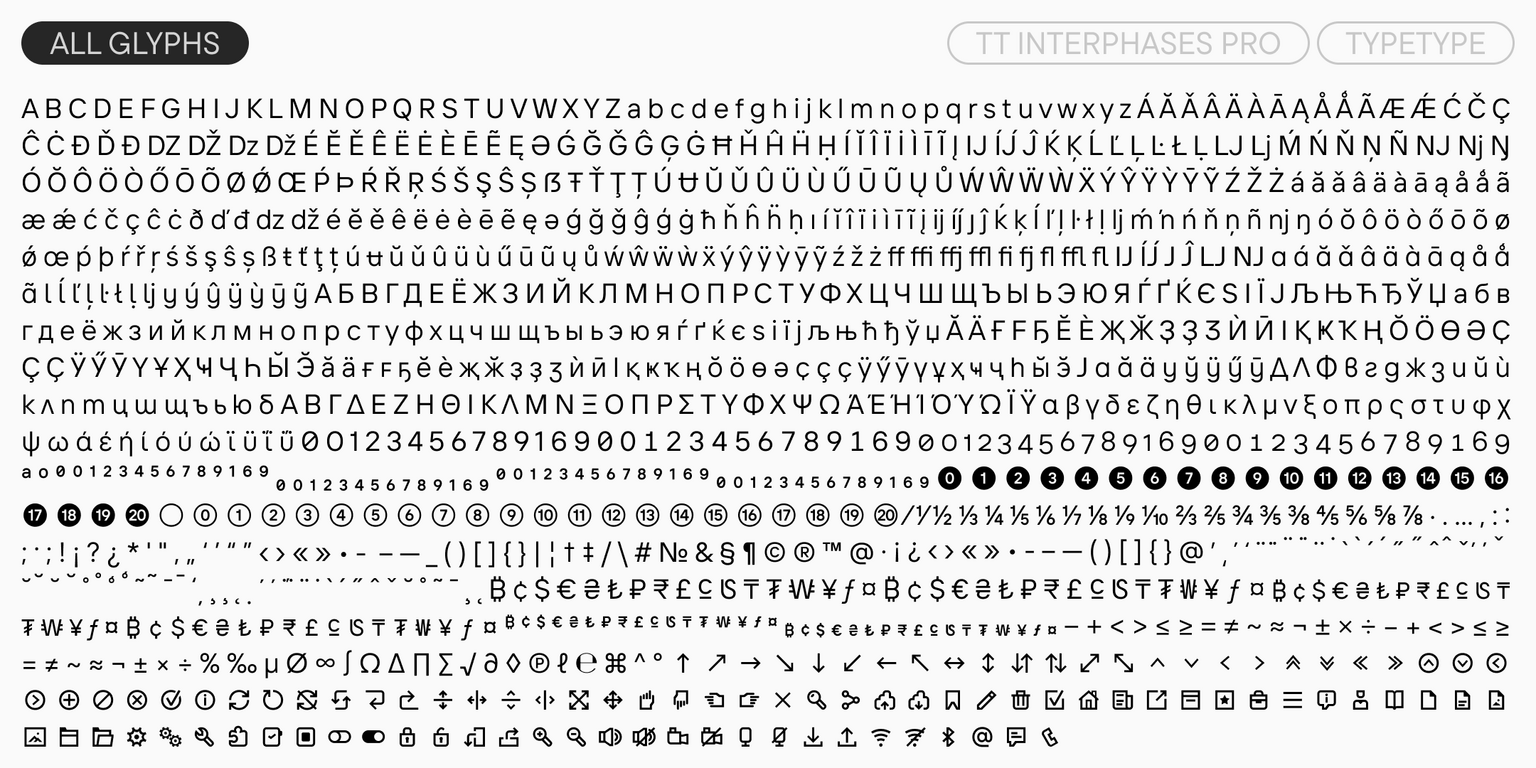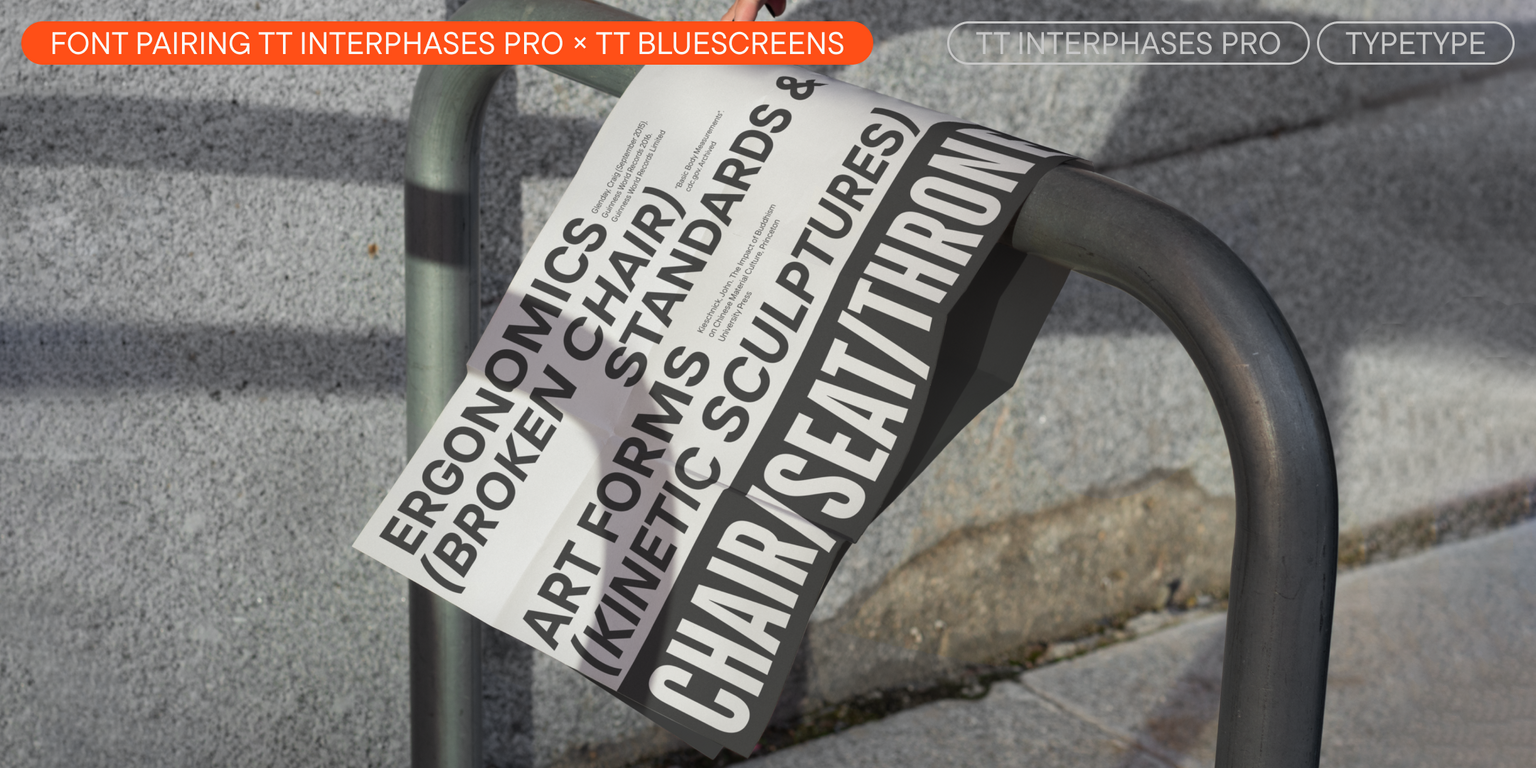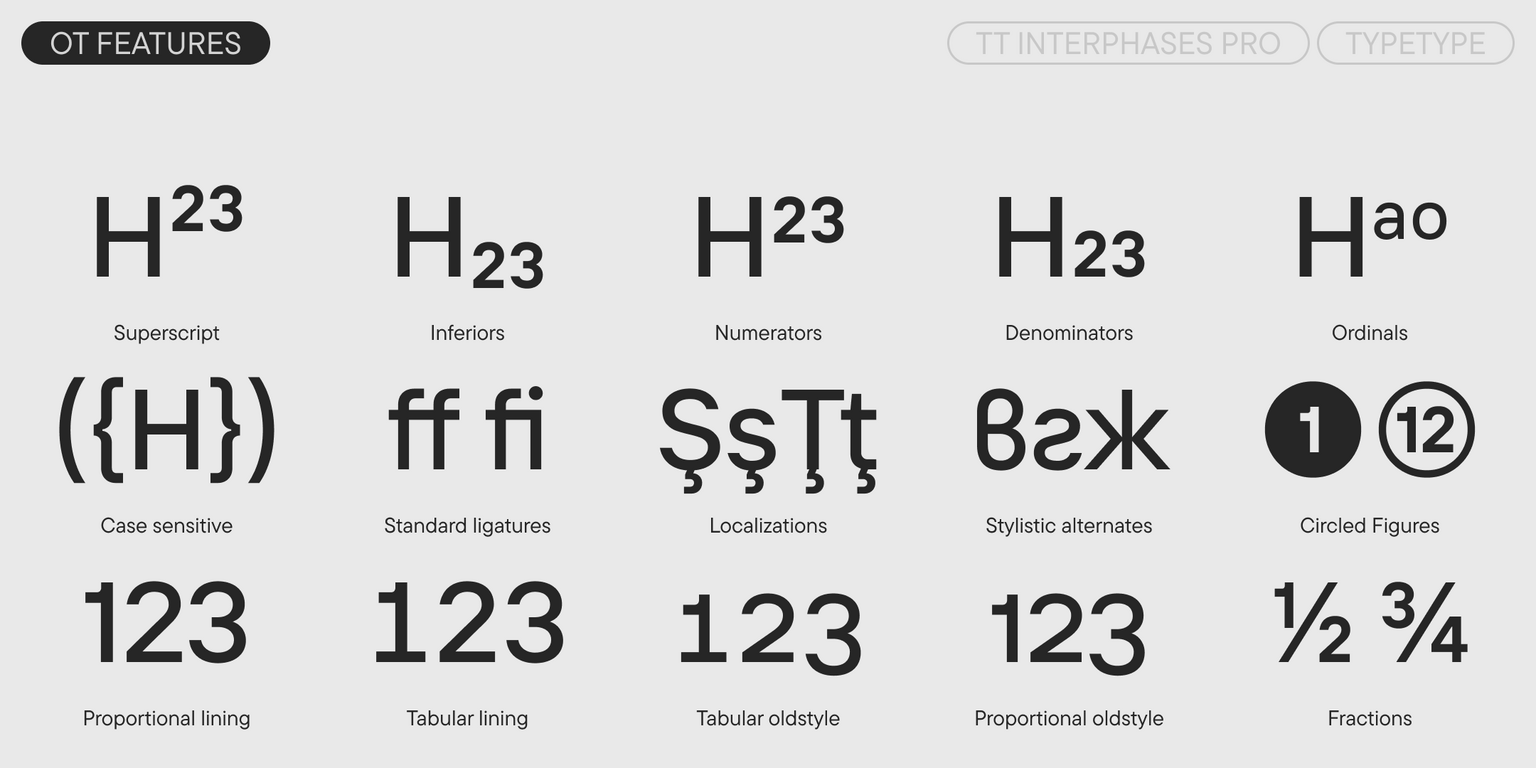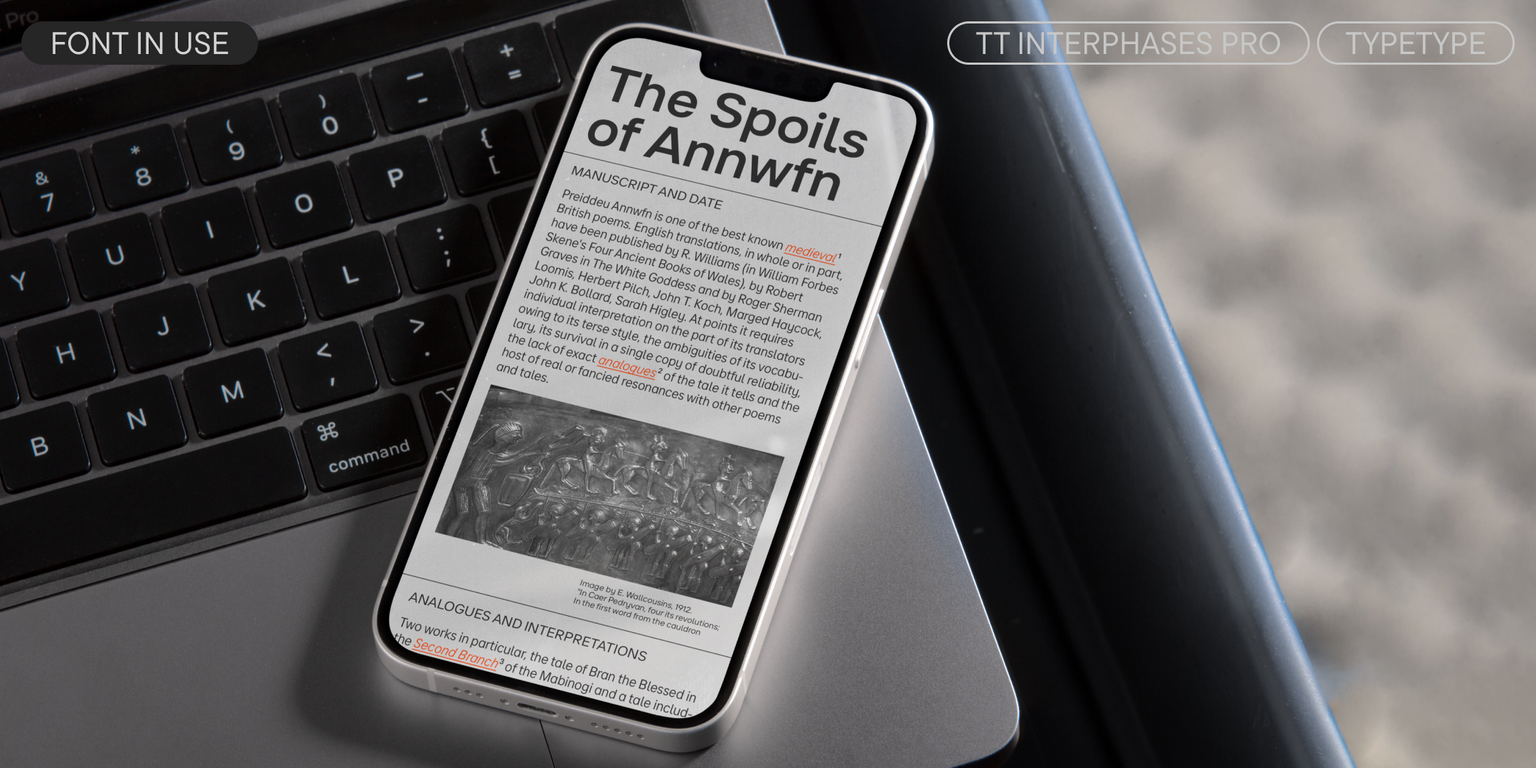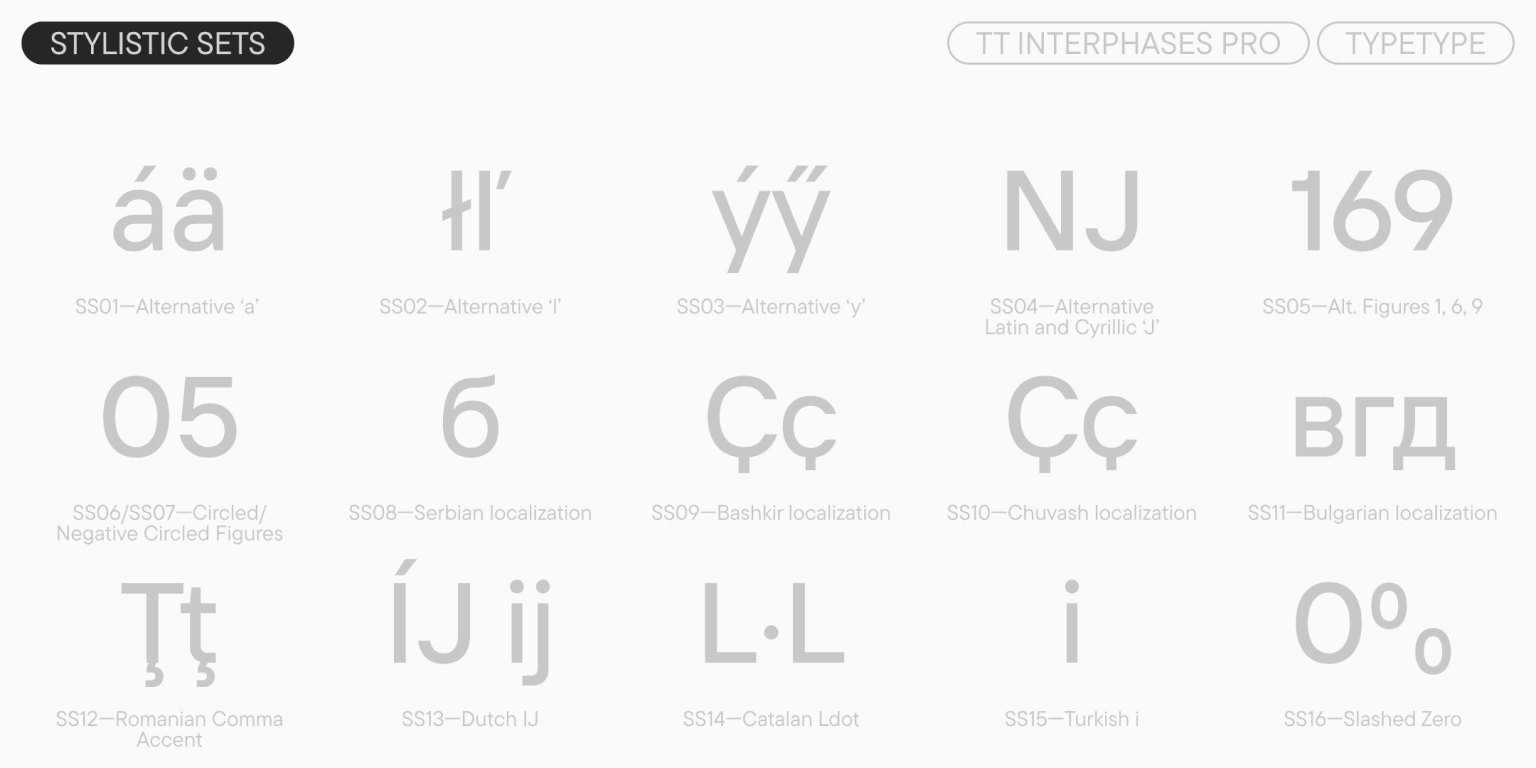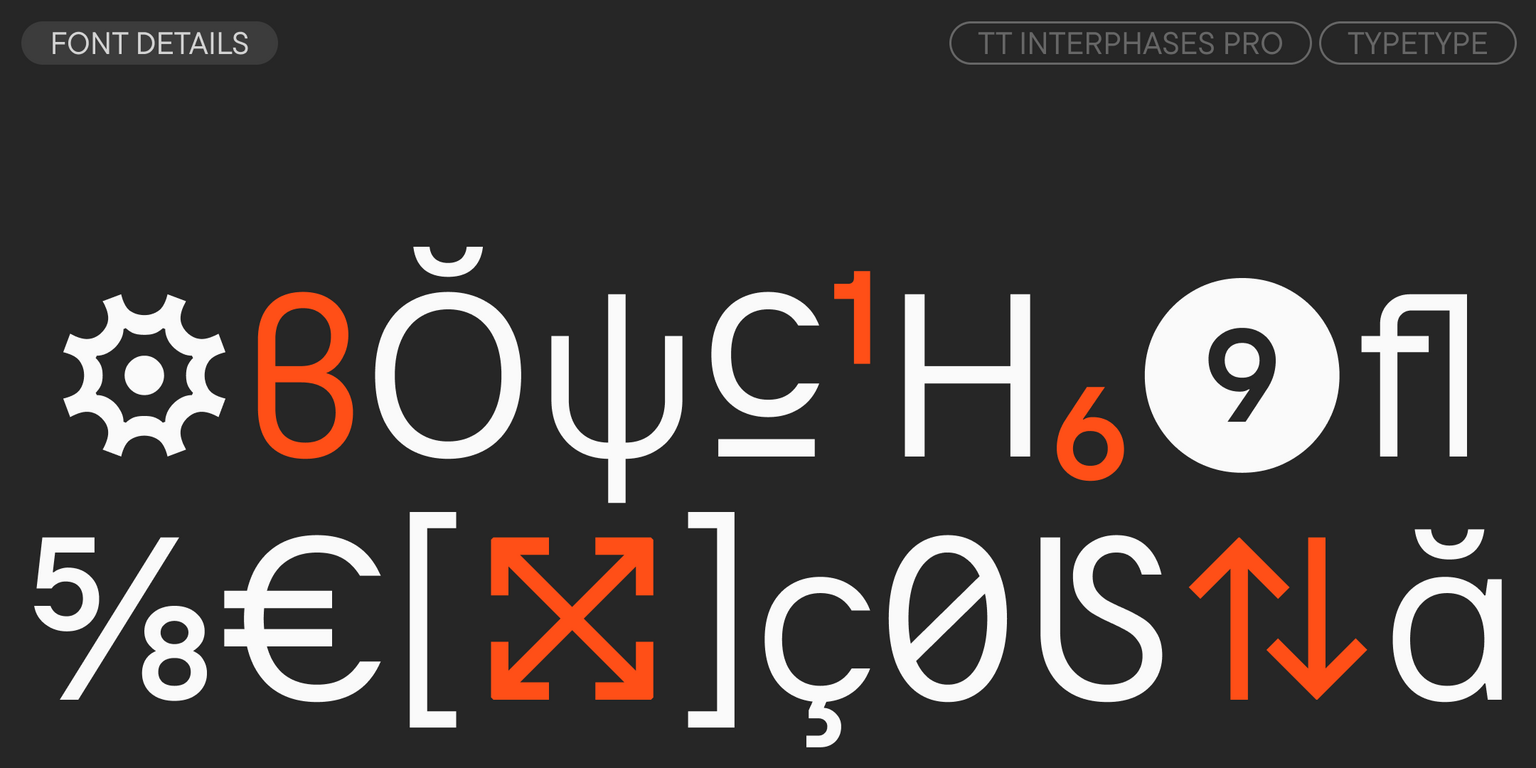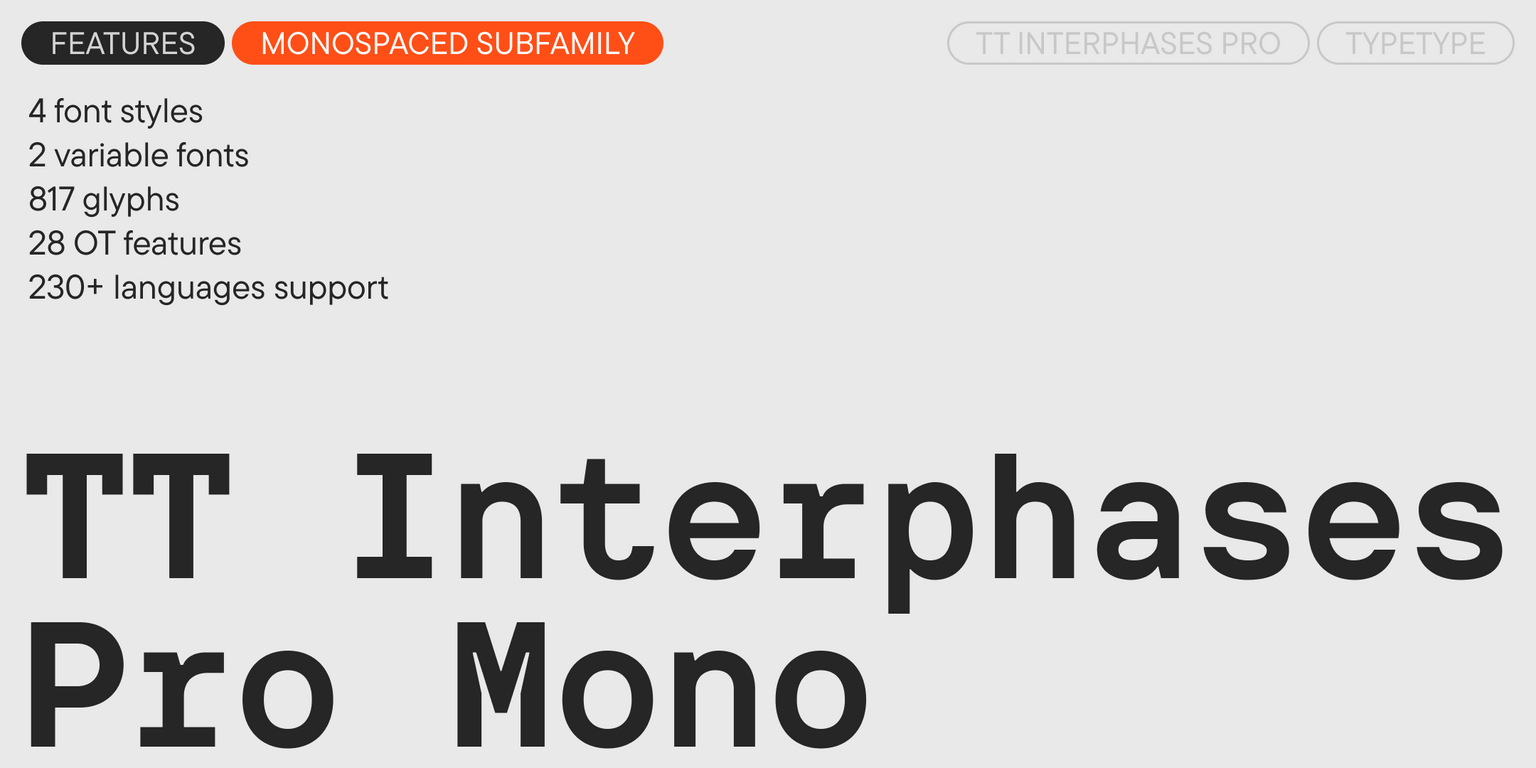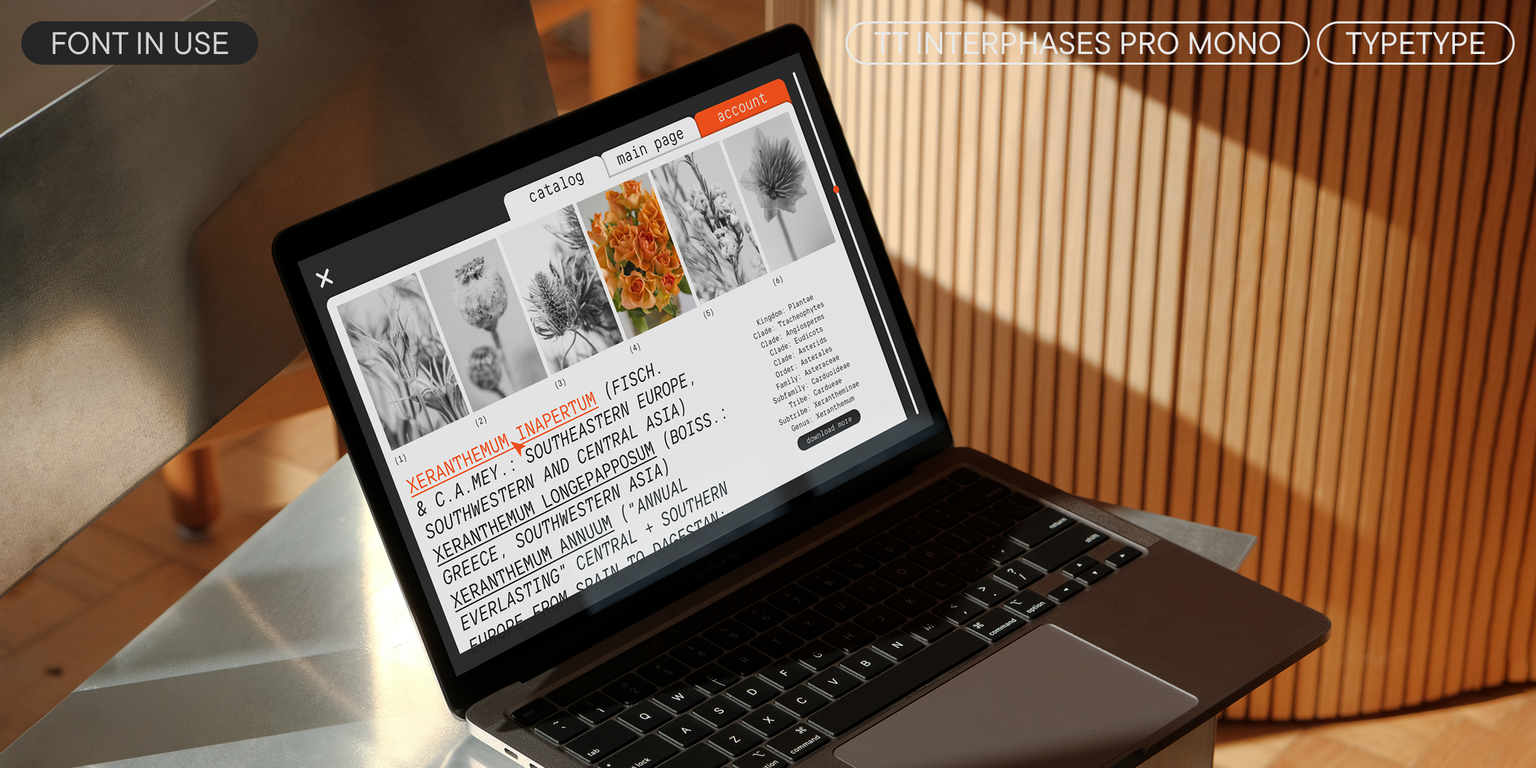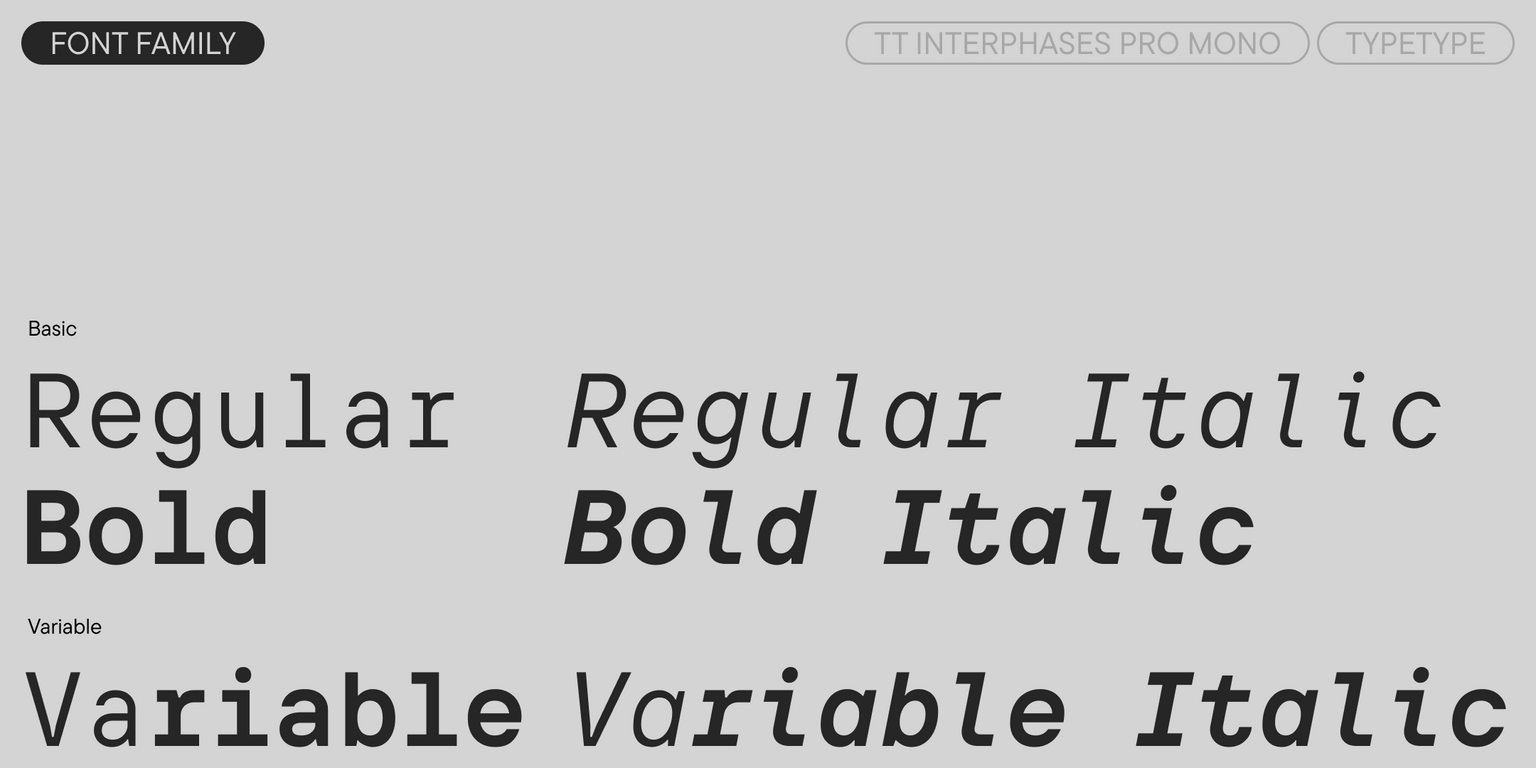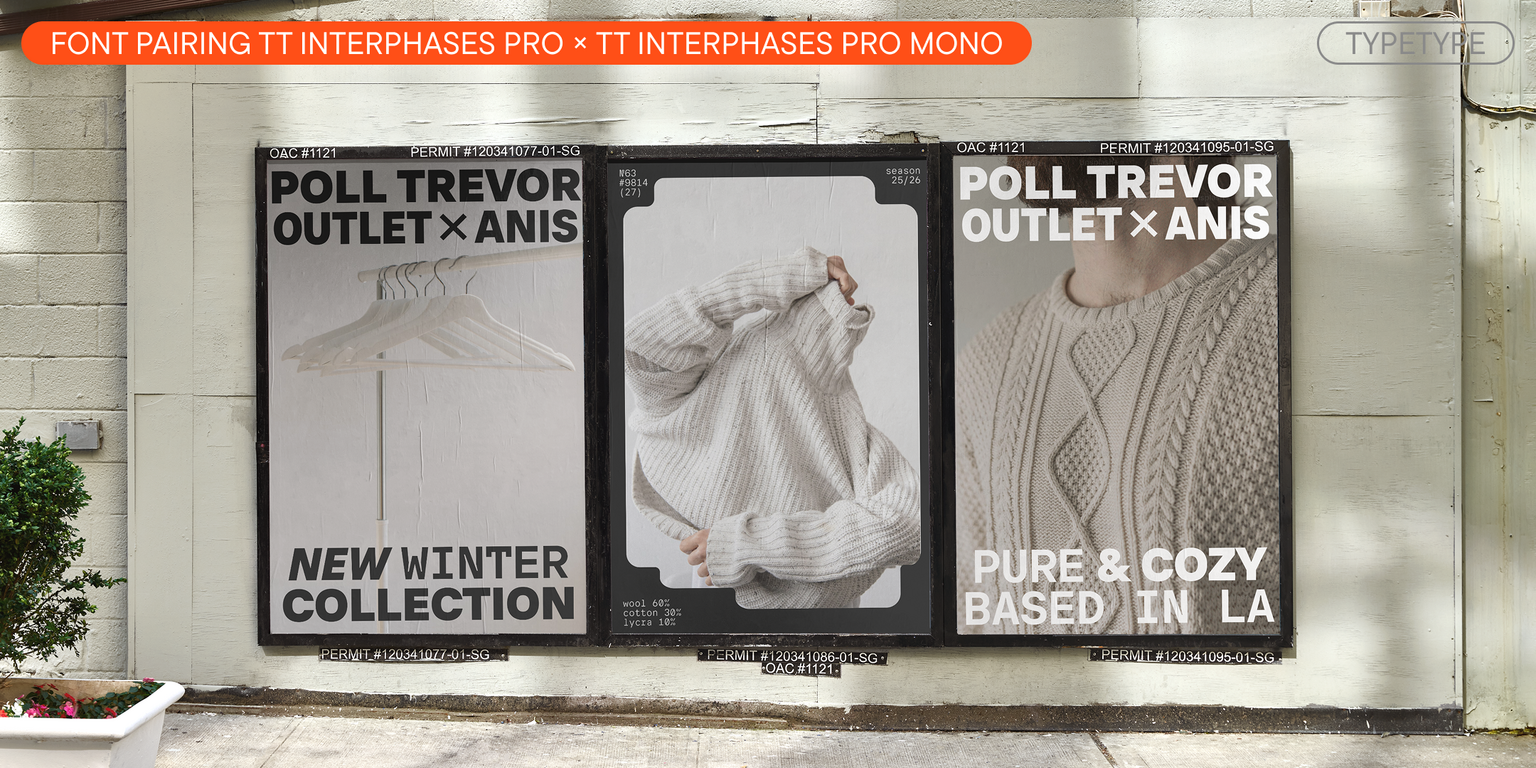
TT Interphases Pro — نوجروتيسك تم تصميمه خصيصًا للعمل في الواجهات. إنه خط أنيق ومختصر ووظيفي، سيشكل أساسًا لأي منصة.
Mathematically precise font for works in interfaces
This typeface is a universal and convenient tool for designers who actively use interface fonts in their projects. At the same time the typeface is beautiful, elegant, but invisible and neutral. From the technical point of view, TT Interphases is perfect, have the most modern hinting, as well as a variable version for those who are well versed in the subject. We took this project very seriously and, before proceeding with the design itself, we carried out rather exten- sive research work.
Perfect typeface to work in modern interfaces on most known mobile and web platforms
43 styles: 36 styles in the basic family, 4 monospaced fonts, 3 variable fonts
250+ دعم اللغات
تعرف على TT Interphases Pro الإصدار 2.100 — الآن مع دعم للغة اليونانية! لقد قمنا بتحديث خط الواجهة الوظيفي والمريح هذا، مما يجعله أكثر كمالًا.
TT Interphases Pro هو خط من نوع Neo-Grotesque مصمم خصيصًا للعمل مع الواجهات. يظهر النص المكتوب بهذا الخط بشكل متجانس بفضل نسبه الثابتة. يساعد ارتفاع الأحرف الصغيرة الأكبر على تحسين وضوح القراءة على الشاشة، بينما تضمن السمات المحايدة للحروف والأشكال المربعة للأحرف الدائرية بقاءه مقروءًا حتى في الأحجام الصغيرة. توفر أشكال الأقواس الانسيابية اتساقًا عبر جميع العناصر، مما يجعل قراءة كتل النصوص الكبيرة سهلة ومريحة. كما تضفي الفتحات المغلقة على الخط مظهرًا عصريًا ومميزًا.